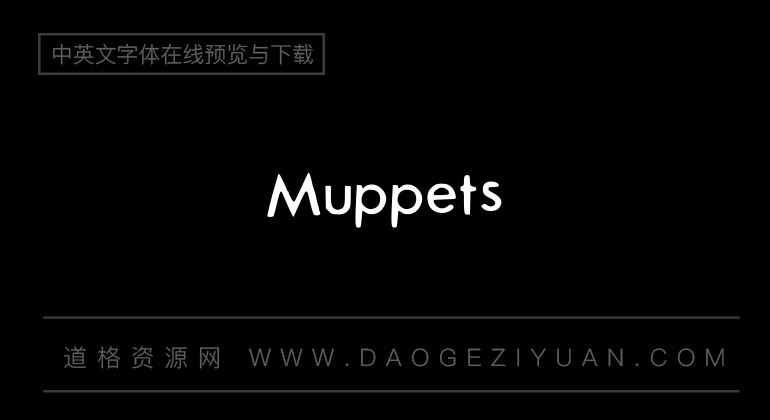
Muppets
"Muppets" 字体是指以同名电影和电视节目中的标志性标语和文字为基础设计的一款字体。这种字体的特点是字母和数字都非常圆润和有趣,具有一种幽默感和童趣感,与Muppets品牌的形象风格非常匹配。 "Muppets" 字体的设计灵感来自于Muppet Show的标志性标语"it's time to play the music, it's time to light the lights"。这种字体非常适合用于儿童书籍、漫画、卡通、广告等领域,因为它能够吸引孩子们的目光,同时也能够表现出一种轻松、幽默的氛围。 "Muppets" 字体由设计师 Jim Henson 和 Michael Frith 开发,在 Muppet Show 的广告、海报和其他推广材料中广泛使用。现在,这种字体也可以在网上免费下载和使用,如果你需要一个有趣、轻松、富有童趣的字体,就不妨试试"Muppets" 字体。
Muppets是一款非常不错的手写艺术字体,具有很好的视觉感,适合于文化类的宣传设计、商业类品牌的广告和产品包装设计以及个性化文字排版等较多场景。